싸인은 단순한 서명이 아니라, 나를 표현하는 하나의 상징이예요. 간단하지만 강렬한 싸인은 사람들에게 깊은 인상을 남길 수 있죠. ✨
많은 사람들이 멋진 싸인을 원하지만, 복잡하면 오히려 인식하기 어 려울 수도 있어요. 그래서 간단하면서도 강렬한 싸인을 만드는 것이 중요하답니다!
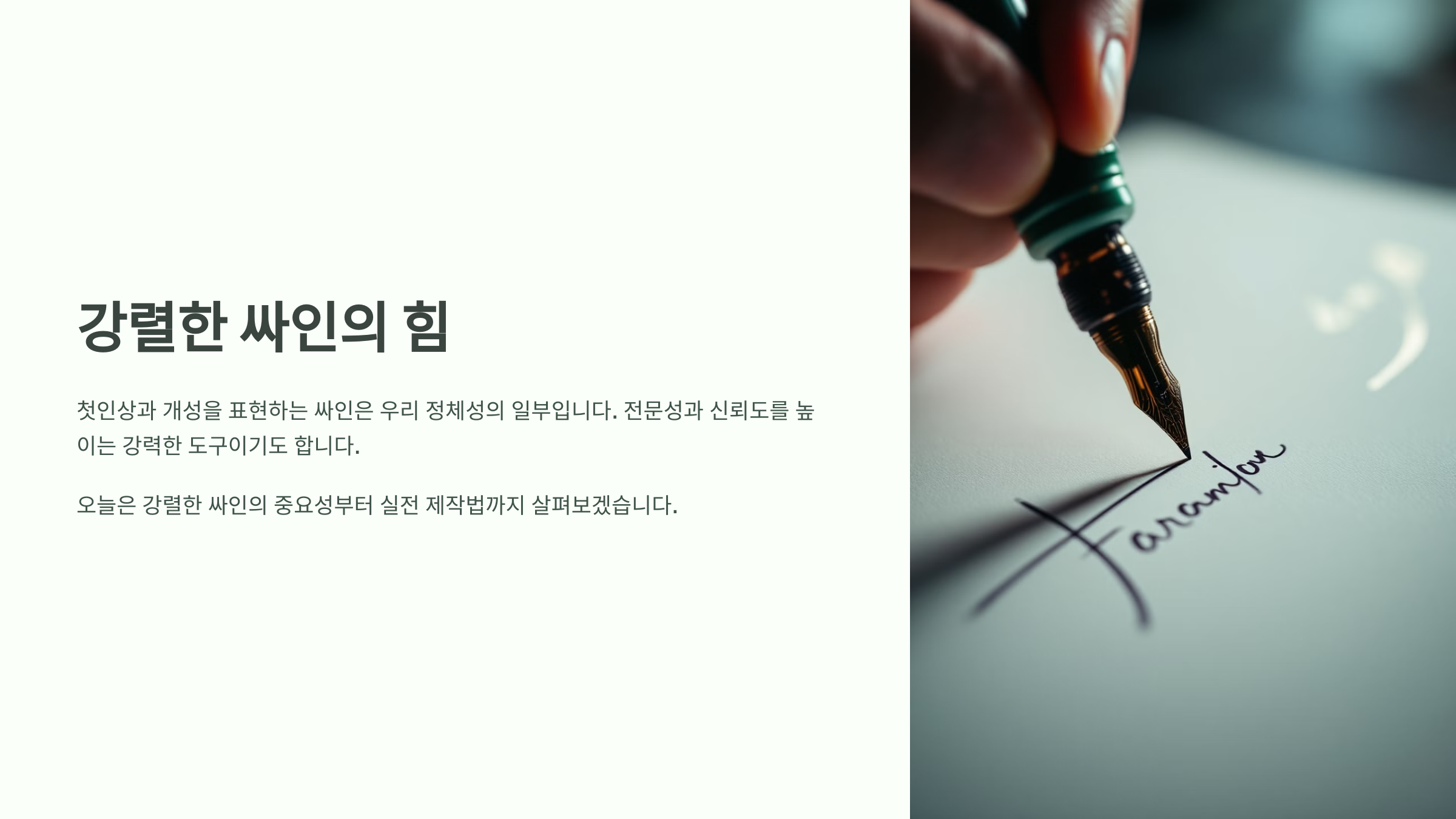
내가 생각했을 때, 강렬한 싸인의 핵심은 ‘고유한 특징’이예요. 단순 하지만 개성이 살아 있는 디자인이 가장 기억에 남거든요. 오늘은 강렬한 싸인을 만드는 공식을 자세히 알려드릴께요!
강렬한 싸인이 중 요한 이유
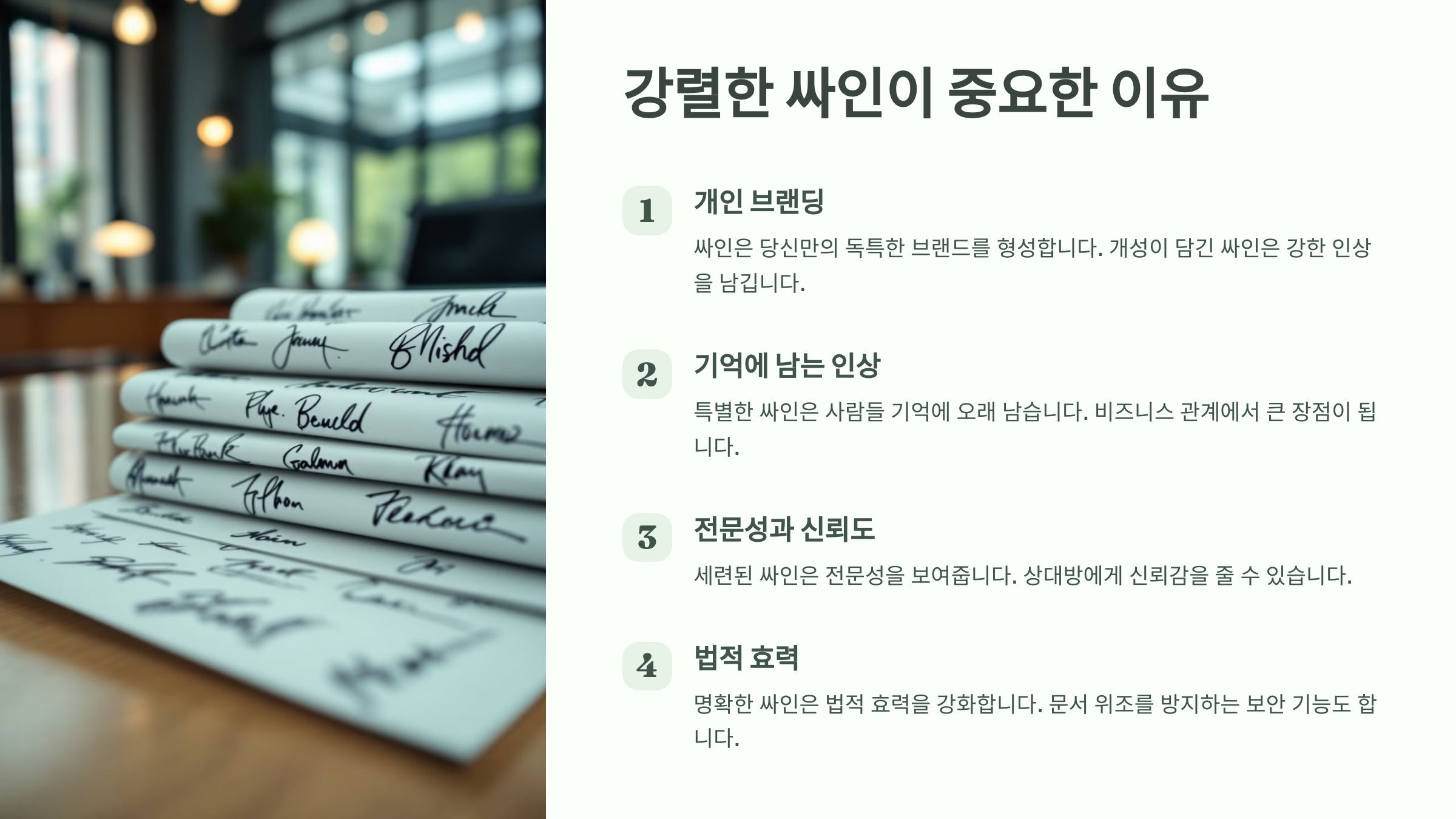
싸인은 단순한 이름이 아니라, 나만의 브랜드가 될 수 있어요. 사람들 이 한 번 보면 기억하는 싸인은 다양한 분야에서 유용하게 쓰일 수 있죠.
예를 들어, 연예인, 운동선수, 예술가들은 싸인을 통해 자신의 브랜드 가치를 높여요. 팬들에게는 기념품이 되고, 비즈니스에서는 신뢰의 상징이 되기도 하죠.
강렬한 싸인이 필요한 이유
이유 설명 개성 표현 싸인을 보면 그 사람의 성격을 알 수 있음 브랜드 가치 유명인 의 싸인은 브랜드화될 수 있음 보안 및 신뢰 공식 문서나 계약서에서 중요한 역할 이제 강렬한 싸인을 만들기 위해 필요한 핵심 요소를 알아볼까요?
강렬한 싸인의 필 수 요소 ✅
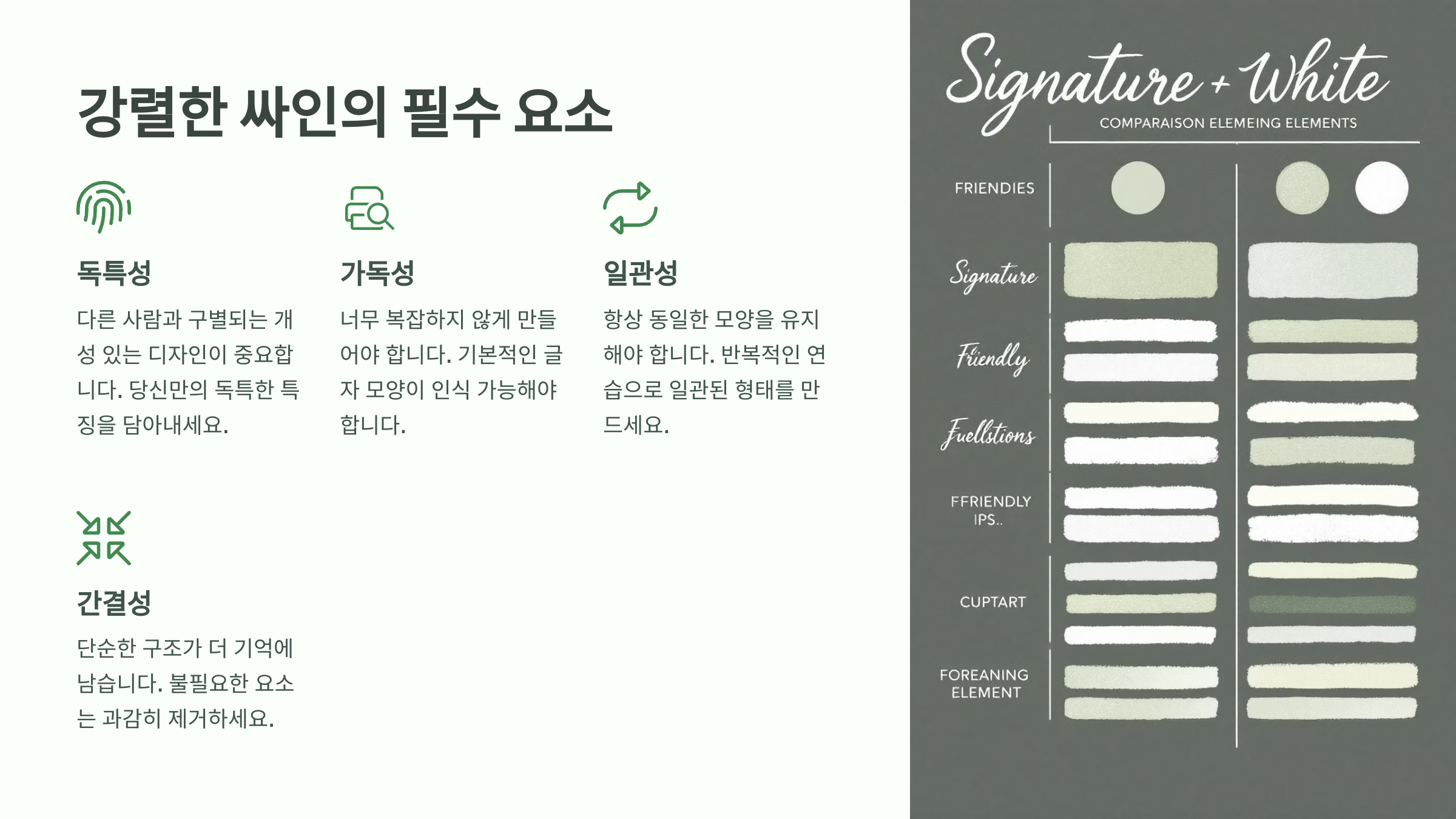
강렬한 싸인을 만들려면 몇 가지 중요한 요소를 포함해야 해요. 단순 히 이름을 적는 것이 아니라, 개성과 독창성을 강조해야 하죠. ✨
예를 들어, 싸인의 길이는 너무 길지 않게 하고, 가독성이 좋은 스타 일을 유지하는 것이 좋아요. 여기에 기호나 숫자를 넣으면 더욱 특별한 느낌을 줄 수 있어요!
강렬한 싸인을 위한 3가지 필수 요소
요소 설명 간결함 한눈에 알아볼 수 있도록 단순하게 독창성 다른 사람과 차별화된 스타일 적용 균형 싸인의 크기와 비율 조정 이제 직접 따라 하면서 싸인을 만들어 볼까요? ✍
한 단계씩 따라 하 는 싸인 제작법 ✍
1. 이름을 기본으로 스케치 연습장에 자신의 이름을 여러 스타일로 써보세요. 필기체, 대문자 조합 등 다양한 방법을 시도하는 것이 좋아요.
2. 고유한 특징 추가 이름의 첫 글자를 강조하거나, 끝에 곡선을 넣어 독창적인 스타일을 만들 수 있어요. ✨
3. 숫자나 기호 활용 자신만의 행운의 숫자나 특수 기호(★, ∞, ♡ 등)를 추가해 더 멋지게 꾸며보세요.
4. 크기와 비율 조정 싸인이 너무 크거나 작으면 가독성이 떨어져요. 적절한 크기로 조정하는 것이 중요해요.
5. 반복 연습 싸인을 자연스럽게 쓸 수 있도록 반복해서 연습하세요. 손에 익으면 더욱 세련되게 보일 거예요!
FAQ ❓
Q1. 싸인은 꼭 필기체로 해야 하나요?
A1. 아니요! 필기체가 아니어도 괜찮아요. 자신만의 스타일이 가장 중요해요.
Q2. 싸인을 너무 복잡하게 하면 안 되나요?
A2. 너무 복잡하면 가독성이 떨어지고 기억하기 어려울 수 있어요. 간결하면서도 개성 있는 스타일이 좋아요.
Q3. 싸인에 숫자를 넣어도 될까요?
A3. 네! 숫자를 추가하면 더욱 특별한 느낌을 줄 수 있어요. 예를 들어 ‘KJ23’처럼 사용할 수 있어요.
Q4. 싸인을 자주 바꿔도 되나요?
A4. 가능하지만, 공식 문서에서는 동일한 싸인을 유지하는 것이 좋아 요. ⚠
Q5. 싸인을 연습하는 가장 좋은 방법은?
A5. 종이에 여러 번 써보면서 자연스럽게 익히는 것이 좋아요. 손에 익으면 더욱 멋진 싸인이 돼요! ✍
Q6. 싸인을 만들 때 참고할 만한 스타일이 있나요?
A6. 유명인의 싸인을 참고하되, 그대로 따라 하기보다는 자신만의 개 성을 더하는 것이 좋아요.
Q7. 싸인을 디지털로 만들어도 되나요?
A7. 네! 태블릿이나 전자 서명 프로그램을 활용하면 디지털 싸인도 만들 수 있어요.
Q8. 싸인을 더 세련되게 보이게 하는 방법이 있나요?
A8. 글씨의 필압을 조절하거나, 선의 굵기를 조정하면 더욱 멋진 싸 인이 돼요! ✨